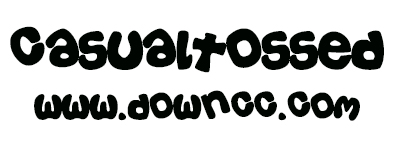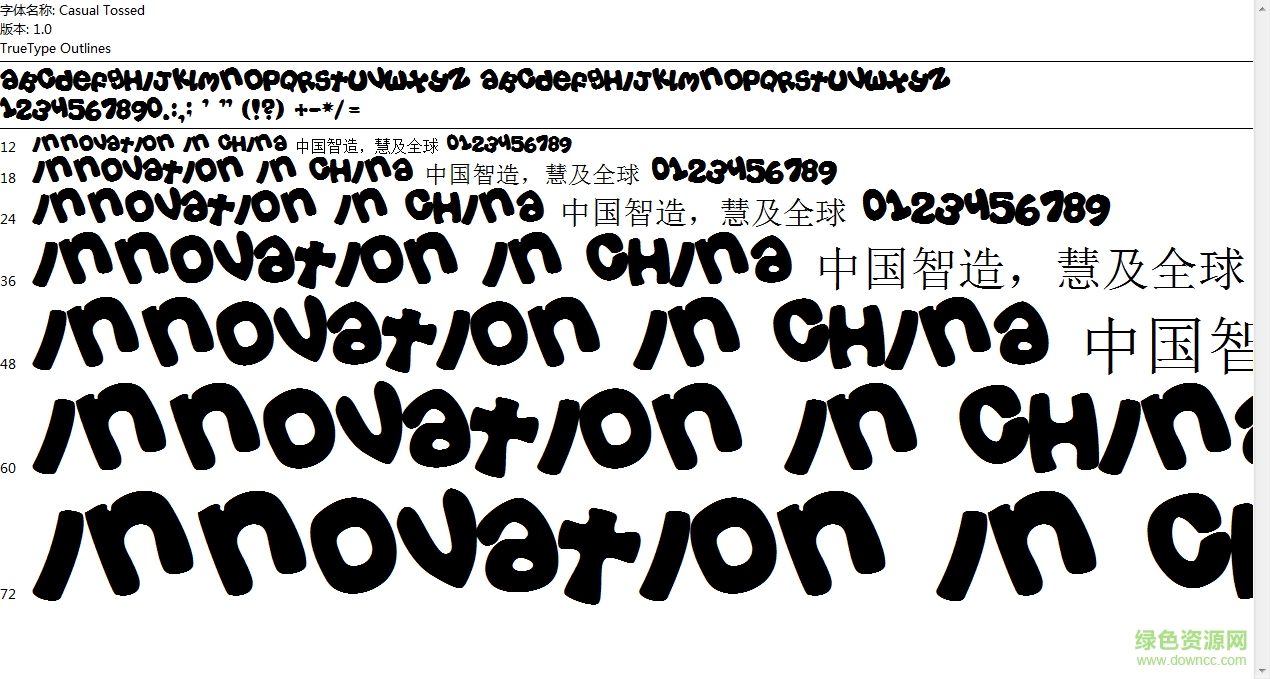
casualtossed字體是網(wǎng)友們比較喜愛(ài)的一款卡通字體。字體看起來(lái)東倒西歪的,像一只只活潑好動(dòng)的貓咪!適用范圍非常廣。喜歡的朋友歡迎來(lái)綠色資源網(wǎng)下載!
casualtossed是一款不規(guī)則的英文字體,此款字體比較俏皮可愛(ài),有著有沒(méi)的比例,十分受大眾喜愛(ài),廣泛擁有與排版、平面設(shè)計(jì)、動(dòng)漫等領(lǐng)域!